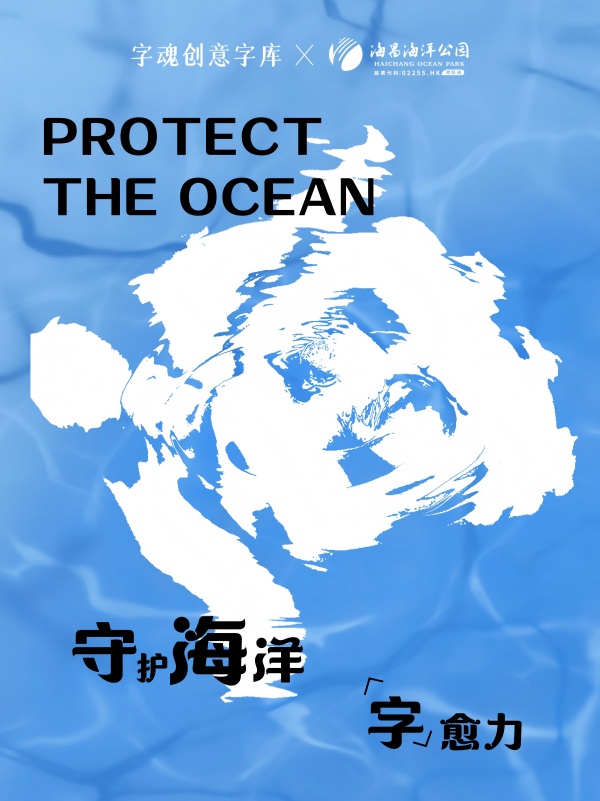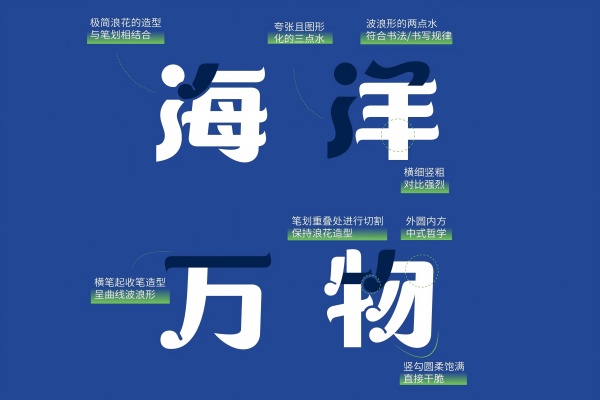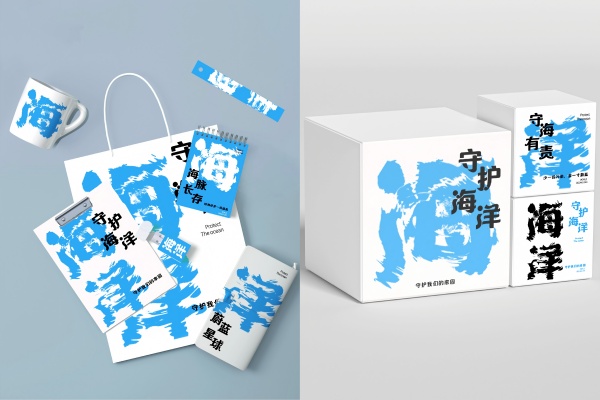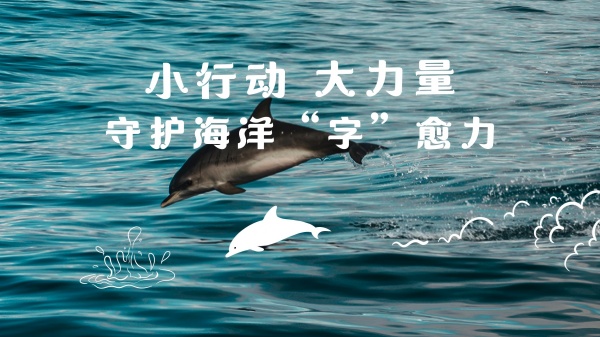
字魂海昌海洋体:定制字体助力品牌价值传递
在品牌竞争日益激烈的今天,定制字体已成为企业塑造独特视觉身份、传递品牌价值的重要工具。关于字体和品牌之间的关系,字库公司与神经科学公司Neurons此前的调研结论显示,合适的字体设计不仅能提升13%的品牌好感度,更能通过视觉一致性强化消费者认知,建立深层次的情感连接。例如,上海交响乐团的定制字体——“字魂上海交响乐谱体”融合了静态文字与动态音律,让文字承载着乐团百年理念与城市情怀,成功唤起消费者的情感共鸣,并荣获伦敦设计奖银奖,进一步印证了定制字体在品牌叙事中的关键作用和品牌价值的深层次传递。
而在2025年世界海洋日,字魂以⌈字愈海洋⌋为主题,推出为海昌海洋公园特别设计的定制字体——字魂海昌海洋体。此次的字体设计不仅进行了创意的碰撞,也传递了品牌在海洋生态保护领域的理念,彰显出企业的社会责任与价值。
大海拥有神奇的自愈力,为人类提供丰富资源的同时,也维持着海洋种群的稳定存续。
然而,人类的过度索取让这片蔚蓝日渐疲惫,恢复生机的速度大不如前。基于本次与海昌海洋公园的跨界联动,字魂创意字库期望以创意且温暖的方式,唤起人们对海洋更多的关注与保护。
“让文字成为人与海洋的纽带,让设计的灵感推动关爱的传播”,这是字魂海昌海洋体诞生的初衷。设计团队提取了人们心中描绘海洋的关键词,将其融入独特的字体设计中,期望在一笔一画间重新搭建人与自然的共鸣。
字体形态的构建上,字魂字体设计团队深度解构了海洋生态的有机美学,巧妙地融入了海浪造型与海洋生态中的有机感,波浪的设计概念,让笔画具备动感的曲线形态,横向笔画的起笔收笔,设计成了翘起的小角,象征着流动与活力。圆点、波纹和水花,构成了字体的主要设计语言,而字形内转折处的圆角处理,也让它更有亲切感。笔画交叉处将印刷时代的油墨陷阱技术进行了重译,原本为防止油墨晕染的功能性缺口,转化为跃动的浪花,使其在辨识度和适应性方面都非常好。这款为海昌海洋公园打造的品牌定制字体,既有自然亲和力,又具有视觉张力。
西文部分有一定的卡通感,但并不会过于幼态,带有温暖的人文气息,小写字母的笔画过渡设计,也与汉字叠加海浪处保持了一致,在搭配汉字时更为和谐。
字魂海昌海洋体是符合国标GB2312简体中文编码字符标准的品牌定制字体。全字库包含7144个中文字符,1260个西文及数字符号,共计8404个字符。这款字体可以被广泛地应用于海昌海洋公园的线上宣发与线下乐园及文创产品等丰富的使用场景中。
“人与自然本来就共生共融,将来自海洋的设计应用于日常,使得文字在传递信息的同时,也能成为可持续理念的载体。”
字魂创意字库的设计师表示:团队最大的目标,就是将蔚蓝领域的天然之美与生命力量,通过笔触抵达人们的心中,使得每一个使用字体的人,都能感受到与海洋生命的联结。
同时,字魂和海昌海洋公园还一同发起了 UGC 创作活动,邀请用户使用字魂海昌海洋体,制作与海洋公益有关的作品发布至小红书,让更多人成为海洋保护倡导者的一员。
这种方式充分调动了公众的参与感与积极性,也让海洋保护的理念通过创意作品得以广泛传播,使得字体设计不仅是一种艺术表达,更成为了推动海洋保护的实际力量。
当下,传播方式的多样化,使得字体的应用场景越来越广泛。字魂海昌海洋体凭借其独特的设计理念和特征,不仅能够在传统的平面设计中发挥作用,还能在新媒体、数字艺术等领域展现出独特的魅力。